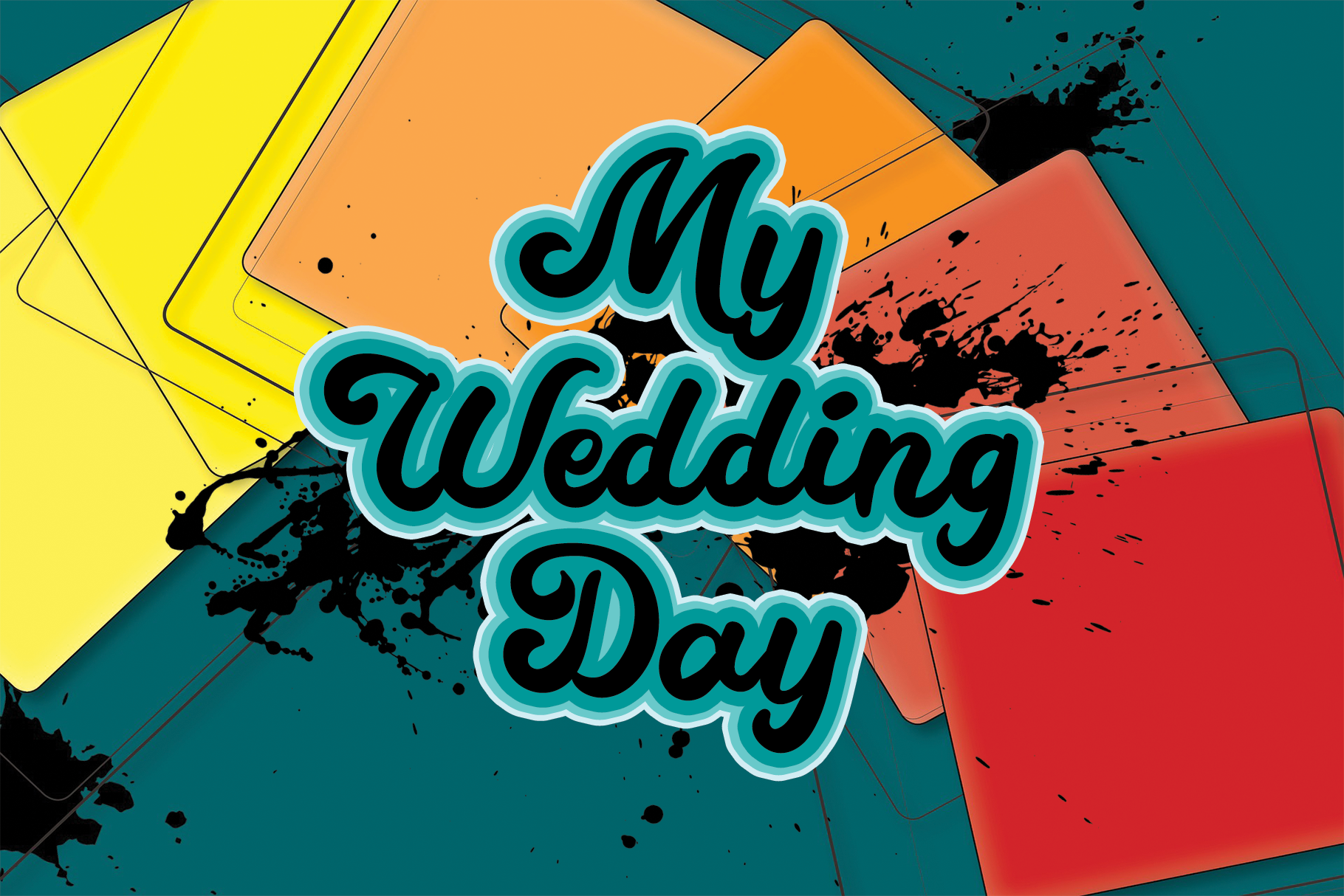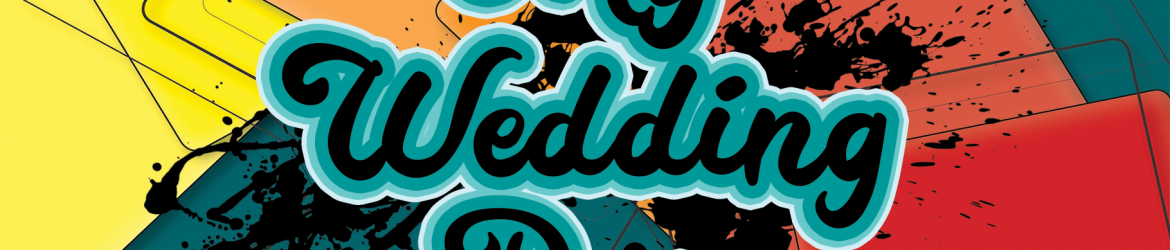
My Wedding Day Font – Download Grátis
Essa é uma fonte de escrita manuscrita inigualável e bela, com um estilo retro que encantará seus olhos desde a primeira vista. Ela transmite uma sensação romântica e autêntica, perfeita para personalizar suas lembranças mais queridas. Especialmente ideal para o dia do casamento, essa fonte será capaz de dar um toque único aos teus projetos, elevando-os a um novo nível. Desenvolvida pelo designer el hotcig, esta fonte é perfeita tanto para gravação de vídeos de casamento quanto para personalizar mensagens de e-mail ou até mesmo artesanato. Suas linhas leves e elegantes combinam com qualquer estilo que você escolher, tornando-a uma opção versátil que se adapta a diversos projetos. Assim que tiver a chance de experimentar esse charme único, certamente não irá desistir de sua versão manuscrita.